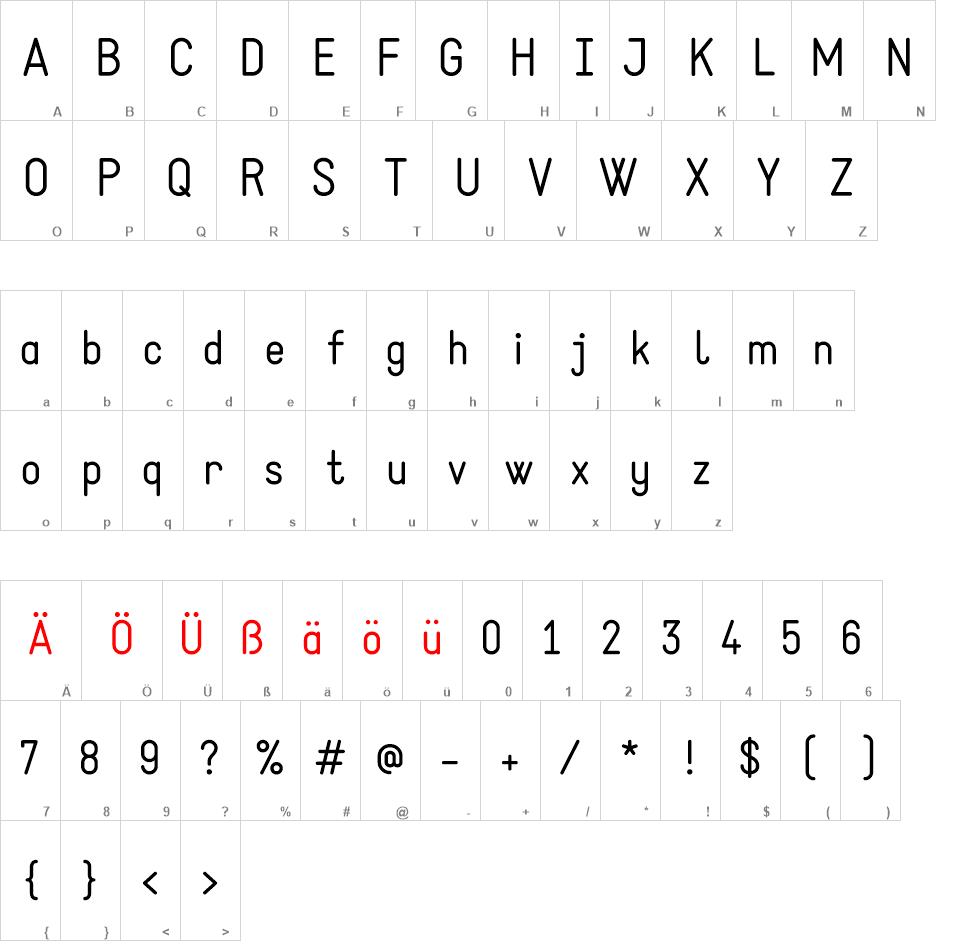
Static
Static font
Statischer, monospaced Stil ist eine zeitgenössische freie Schrift, die mit starken geometrischen Formen erstellt wurde. Geeignet für alle Arten von Grafikdesigns - Web, Print, Motion Graphics usw. Und es ist perfekt für T-Shirts und andere Artikel wie Poster, Logos.